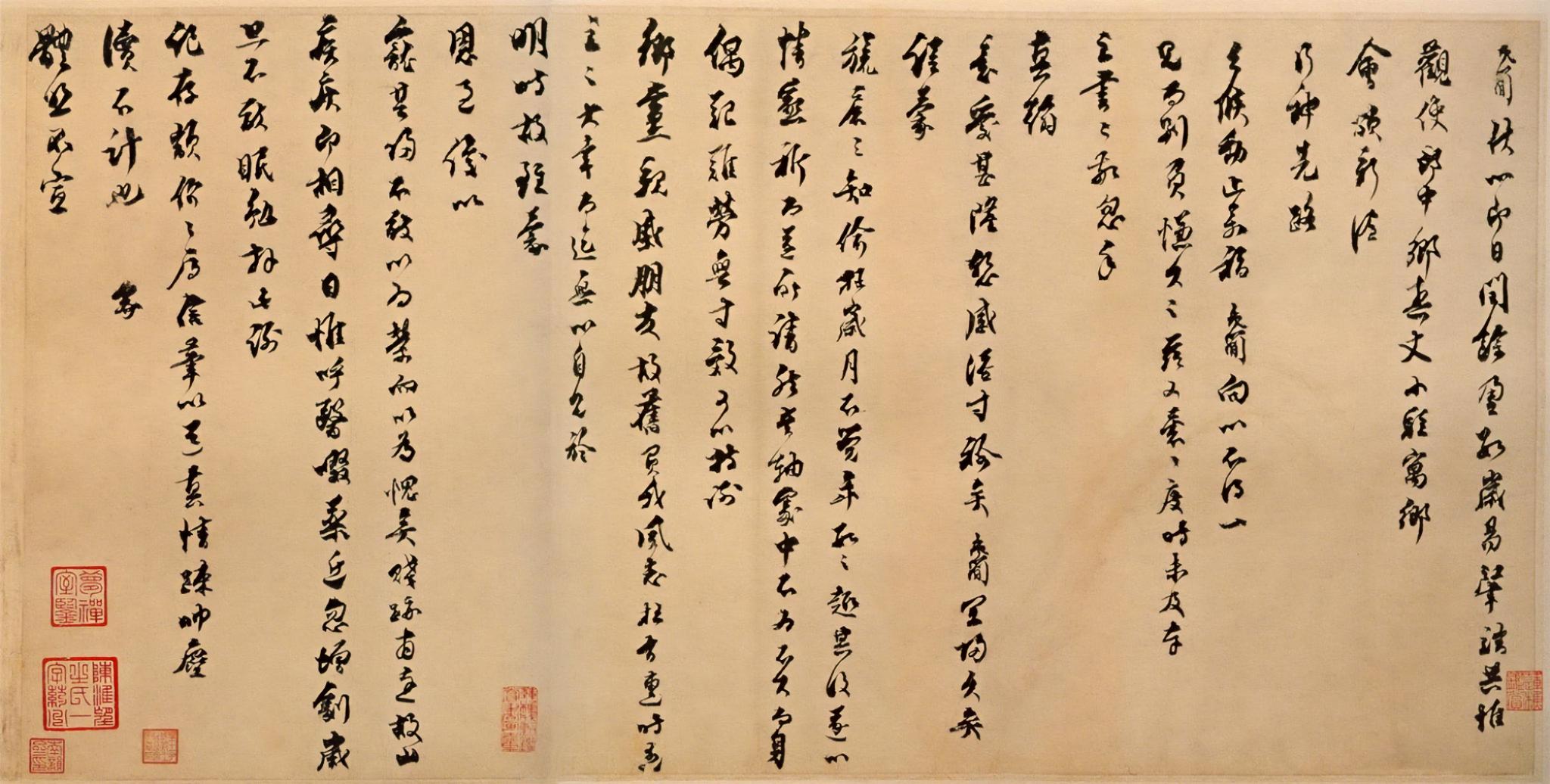
字体全名: 汉标乔行简行书闰余帖
字体简介: 下载须知:本字库非标准GB2312字库。本字库只包含了乔行简《闰余帖》真迹上的“286个字”。本幅鉴藏印钤“莲樵鉴赏”、“皇十一子成亲王诒晋斋图书印”、“莲樵成勋鉴赏书画之章”、“南韵斋印”、“梦禅室鉴”、“陈淮望之氏一字药州”。《闰余帖》,宋,乔行简书,纸本,册页,纵32.1厘米,横42.5厘米,行书,23行。《闰余帖》又称《观使郎中帖》。